说起在世界范围内有影响力的西文字体,人们通常会想到由瑞士人设计的Helvetica字体、由法国人设计的Garamond字体、由意大利人设计的Bodoni字体、由德国人设计的Futura字体……其实,在上世纪50年代,也有一套由中国人设计的拉丁字母印刷体在国际上崭露头角并屡获殊荣,它就是由亚洲地区第一位谷腾堡奖获得者余秉楠先生设计的“友谊体”。这套字体是余先生在德国留学期间设计完成的,1963年,“友谊体”的铜模和铅字被德方作为国礼赠送给中国文化部。然而,这套象征中德两国友谊、有着重要历史意义的西文字体,却没有像Helvetica等字体那样的好命运——被广泛使用并被誉为经典,它甚至不为国人知晓……这其中有着怎样不为人知的曲折故事?“友谊体”的现状又如何?答案将为你一一揭晓!
“友谊体”的由来
1953年,余秉楠先生考入了鲁迅美术学院,在那里打下了坚实的专业基础。1956年,23岁的他以优异的成绩从鲁迅美术学院毕业,并通过文化部的考试被派往前民主德国的莱比锡平面设计与书籍艺术大学深造。莱比锡平面设计与书籍艺术大学是一所有着悠久历史的欧洲名校,它有世界顶级水平的书籍设计专业,选择这一专业的学生要经过严格的训练。余先生一进学校,就被要求先写上几个月的字,也不临摹,就是写。二十六个字母,先写正的,再写斜的,然后写小写,来回的写。结构弄好了,笔形对了,就开始写各种各样的字体。写了五、六个字体以后,结构方法都记住了,别的字体看一眼就可以写了。写着写着就慢慢形成自己的风格,慢慢就可以设计自己的作品了。
1959年,前民主德国总理格罗提渥访华,恰逢中国汉语拼音化,他受周恩来总理之托,为中国培养一位能设计拉丁字母印刷字体的留学生,他将这一任务交给了余先生的老师阿尔贝特•卡伯尔教授,而余先生正是教授眼中能够担负此重任的最佳人选。为了不让余先生紧张,卡伯尔教授没有向他说明原委,但有意识在这方面培养他,并要求他设计一套能满足多种用途的拉丁字母印刷体。
之前艰苦的专业训练成为了余先生创作的完美前奏。在创作这幅字体时,余先生首先研究了古典的欧洲文字传统,把有关罗马大写体的大写字母比例运用于现代的设计稿上,相应的小写字母则像所有的拉丁小写字母一样来自卡罗琳小写体,经处理,与大写字母相适应;之后,他用竹子自制了书写工具,经过无数次的书写练习和探讨,通过一定的笔的按压,从上面的字脚开始到下面的字脚,流畅的字脚产生了典型的中国的特征,一种引人注目的风格。
设计过程中,卡伯尔教授常常在艺术原则上不断给余先生启发,他总是强调字母形体的艺术源泉——自然的书写,并说对这一点哪怕有一时的疏忽,也会使全套字母走了样。值得一提的是,卡伯尔教授还专门为余先生请来了有着五、六十年刻字经验的退休老师傅奥托•艾尔勒,负责具体指导他的设计,艾尔勒老师的辅导令余先生受益匪浅,他充分体会到设计问题到了最后是要解决与技术相关的细节的,而这一点仅凭课堂学习显然是无法完成的。
三个月后,中国人自己设计的第一套正体的拼音字终于诞生了。在它投入生产的过程中,艾尔勒老师经常亲自刻模和下厂指导,保证了成品达到字稿的艺术水平。这套活字来得不平常,它融汇了上百个德国劳动人民的智慧,也是中德两国人民友谊的结晶。因此,同在德国留学的余秉楠的中国同学们一致给它取了个象征性的名字——“友谊”。
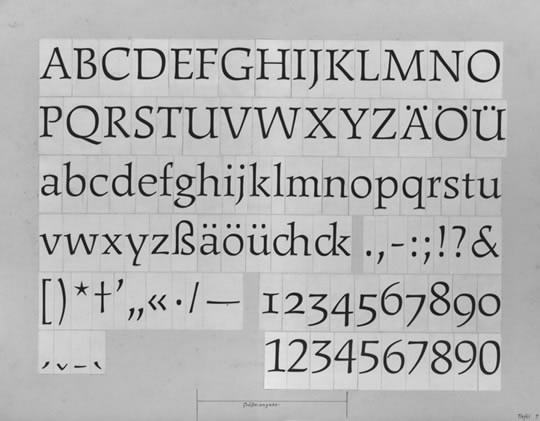
友谊体字样
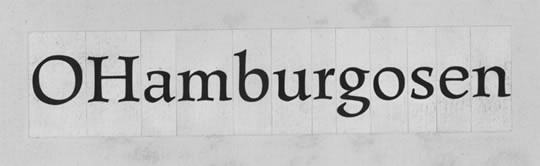
友谊体字样
“友谊体”的中国味道
这套字体的初稿完成后,卡伯尔教授很满意,他把它拍成照片,拿给几个不知情的联邦德国设计师看,得到的回答是:像是一个中国人写的,这让卡伯尔教授感到很惊讶。
拉丁字母在中国还是个新东西,没有先例可以借鉴,如何使它具备自己的特色并表现中国的民族风格是余秉楠苦苦思虑的问题。在深入思考和反复推敲后,他做出了大胆的尝试:把中国书法中线条流利活泼、含意深远、一气呵成的特点以及中国传统图案纹样结构紧密、富于变化、柔婉而又明朗的精神运用到设计中,使它们与拉丁字母形体灵活地结合起来;同时,在不破坏字形协调的前提下,把K、R的最后一个斜笔和Q的尾巴画成类似汉字的一捺,加强与中国书法的联想。就这样,“友谊体”的中国味道就跃然纸上了。
后来在德国的应用中“友谊体”也被称为“中国字体”。
“友谊体”的应用与成就
1960年,当这套字体在所有细部都达到成熟时,产生了用9p和28p大小的字体印刷的第一批印刷品,其中有十分优美的《毛主席诗词》,它有汉语拼音文字和德文两个版本,并与书法的原文相对应。
随后余先生又为这套正体设计了斜体,它同样产生于竹笔书写,与直立的正体组成良好的配套字体。之后,这套字体获得了“德国当代最佳印刷字体奖”。在文学书籍、艺术书籍和儿童书籍,还有一般印刷品上的大量应用,证明了它是一套成功的字体,经历半个世纪而没有丧失它的魅力、表现力和易读性。
1989年,余秉楠荣获德国莱比锡市政府颁发的“谷滕堡”终生成就奖,获奖评语是这样写的:“为表彰在书籍艺术的教学、创作和理论方面的杰出成就。” 特别提到的是他曾经设计的“友谊体”。作为第一套由中国人设计完成的拉丁字母印刷字体,“友谊体”的成就及国际影响,由此可见一斑。
“友谊体”的坎坷命运
1963年,也就是余秉楠回国任教于中央工艺美术学院的一年后,在莱比锡大学的一次隆重的仪式上,作为赠送给中国文化部的国礼,德方把“中国字体”的铜模和铅字授予中华人民共和国的大使。这套字模和铅字存放在当时的文字改革委员会(现在已经改名叫语委——国家语言文字工作委员会)。
不久,“文革”开始了,这套字体也就一直没怎么派上用场。“文革”结束后,余先生前去寻找,想把这套字体要回来用于教学,但遍找不见。
1986年,余先生的导师卡伯尔教授要来中国讲课,听说这套字体流失了,他特地从莱比锡平面设计与书籍艺术大学的工厂中又找出这套字体的铅字,连同用它印刷的书籍《毛主席诗词》一起带来中国,与民主德国驻华使馆的大使一起赠送给中央工艺美术学院,存放于学校的印刷厂供教学使用。
1986年在东德大使陪同下卡伯尔教授向学院赠送“中国字体”铅字
80年代末,学校将印刷厂设备卖给了一家县里的印刷厂,其中也包括“友谊体”。得知消息后,余先生和同事一起赶到那家印刷厂,可那些铅字正被放在火里融化,他们抢回来了一部分,但有些已经毁掉了。追回来的铅字存放在学校的地下室里。1999年,中央工艺美术学院合并到清华大学,在后来的搬迁中这套铅字再次丢失,现在已无从查找。
1990年,德国的德累斯顿字体艺术铸字厂决定把“中国字体”数字化,工作启动不久,民主德国和联邦德国就统一了,工厂被原联邦德国的企业家收购,这件事也就不了了之。
由于历史的种种原因,命运坎坷的“友谊体”在国内基本没有用过,更别说为国人所熟知了。
“友谊体”的现状
怀着最后的希望,余秉楠先生把“友谊体”的设计原稿交给了国内最大的字库厂商——北大方正。接下这套有着特殊历史意义和极高艺术价值的字体原稿,一股强烈的民族使命感驱使着北大方正,他们决定不遗余力的做好这款经典字体的数字化开发,使其发扬光大。
在国外,这类工作被称为“经典字体复兴”,字体设计界赫赫有名的Adrian Frutiger、Hermann Zapf、小林章目前都在进行字体名作的改刻工作。改刻工作要保留字体原来具有的字形和魅力,将其从活字印刷时代的铅字技术的制约中解放出来,重新去适应数字化的要求,在数码环境中再现。改刻工作的目标是复兴我们的经典。
负责“友谊体”数字化复兴工作的是北大方正的高级字体设计师——何媛,此前何媛为方正字库的数十款经典、个性化字体设计了配套的西文字体。刚拿到余先生“友谊体”的字稿时,何媛还以为将它数字化会是个轻松的事情,只需对扫描后的字母进行数字化调整即可完成工作,可是在实际的处理过程中,何媛发现事情远比想象的复杂的多。首先,此前的字稿是手写的,一整套字写下来就难免有许多不规范的地方,对此,何媛利用数字化设计技术对整套字体进行了系统规范,并对一些字型进行了优化;此外,在之前的设计中,余先生有很多想突出表现的笔形特点却由于手写的限制没能一一呈现,在这次的数字化设计中,何媛实现了余先生的初衷。
每设计完一版,何媛都会给余先生过目,考虑到余先生年事已高,何媛多次去余先生任教的清华美院,与老人家面对面讨论修改细节。余先生是个要求尽善尽美的人,他经常给何媛提出一些看似微不足道的建议,比如“m和w的左方内白要比右方内白小一些”、“小写u应该比小写n窄些”。正是这一个个的小建议,才使得数字化后的字体完整的保留了原字稿最本质的风格特点。
历时2年多、历经几十次复原性修改,数字化的“友谊体”终于在2012年设计完成了,即将要跟大家见面的这款字体被命名为“方正秉楠体”,它也是方正字库的第一款西文字库。